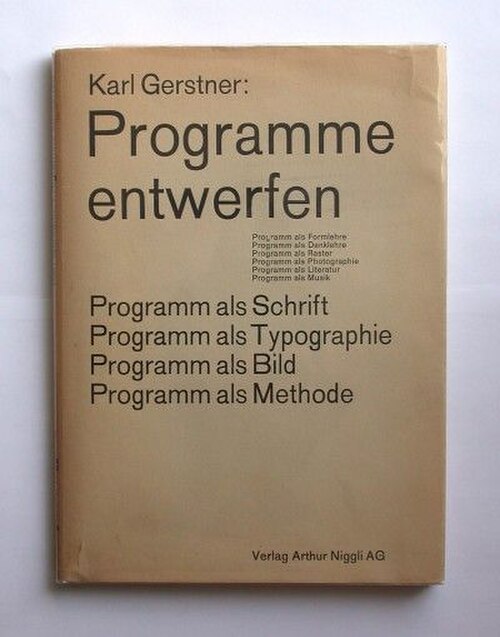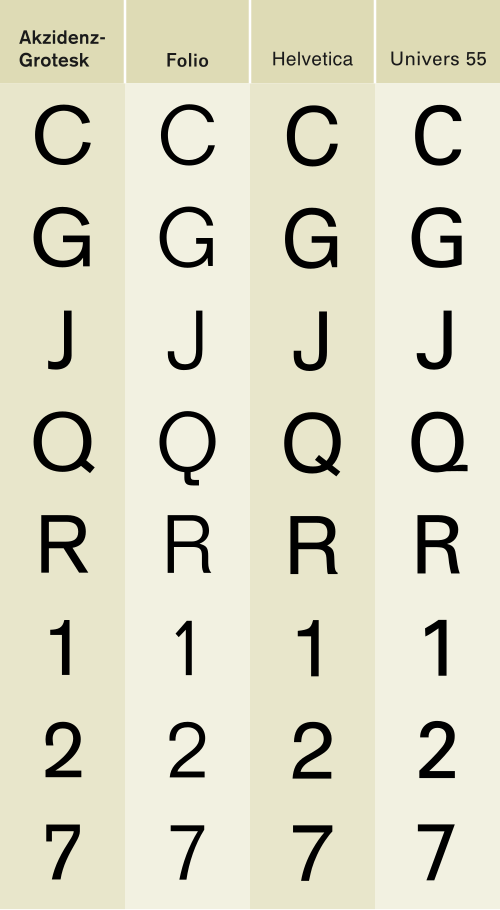
| カテゴリ | サンセリフ |
| 分類 | グロテスク |
| 鋳造所 | H.ベルトルトAG [1] |
| リリース日 | 1898 |
Akzidenz-Groteskは、もともとベルリンのBerthold Type Foundryによってリリースされたサンセリフ 書体ファミリーです。「Akzidenz」は、高級印刷ではなく、宣伝、チケット、フォームなどの商業印刷用の書体として意図されていることを示しており、「grotesque」は当時のサンセリフ書体の標準名でした。
19 世紀後半に誕生したアクチデンツ・グロテスクは、19 世紀にドイツの印刷業界で主流となった、汎用的で飾り気のないサンセリフ体の伝統に属しています。導入後半世紀にわたってあまり知られていませんでしたが、戦後は多くのスイスのグラフィック デザイナーが好む書体として象徴的な地位を獲得し、1950年代から 1960 年代にかけて西側諸国で人気を博した「インターナショナル」または「スイス」デザイン スタイルと呼ばれるようになりました。そのシンプルで中立的なデザインは、その後の多くの書体にも影響を与えました。英語圏の国ではスタンダードとして販売されることがあり、さまざまなデジタル バージョンがBerthold やその他の企業からリリースされています。
語源
アクチデンツ・グロテスクは英語では「jobbing sans-serif」と訳されることが多く、「jobbing」は「仕事に使われる」という意味である。[2]どちらの単語も、当時のドイツ語で書体を表す日常的な用語であった。
Akzidenz は何らかの機会や出来事(「何か起こる」という意味で、高級な社交行事や機会という意味ではない)を意味し[3]、商業印刷の用語として使用されていました。Akzidenzschriftは1870 年代までにこれらの用途を意図した書体を表す一般的な用語になりました。 [3] [4]現代のドイツ語辞書では、広告やフォームなどの作品として説明されています。 [5] [6]この単語の語源はラテン語のaccidentiaで、ルイスとショートはこれを「起こること、偶然の出来事、偶然」と定義しています。 [3] [7]
グロテスク(ドイツ語:Grotesk)は、19世紀前半にサンセリフ体を表す一般的な用語として普及した。1830年頃、ロンドンの活字鋳造業者ウィリアム・ソログッドが、ファン・ストリート鋳造所の見本帳でサンセリフ体を表す名称として導入した。 [8]この名称は、サンセリフ体の「原始的な」感覚、または古代ギリシャやローマの碑文に由来するサンセリフ体を反映している可能性があり、19世紀後半には否定的な意味合いなしに「サンセリフ体」の意味で一般的に使用されるようになった。[8]
デザインの特徴
ほとんどのサンセリフ体と同様に、アクジデンツ・グロテスクは「モノライン」構造で、文字のすべてのストロークの幅が同じです。これにより、シンプルさが感じられ、アール・ヌーヴォー様式の影響を受けた19世紀後半の装飾的なサンセリフ体に見られる装飾や華麗さがありません。[9]現代の書体デザイナーであるマーティン・マヨールは、アクジデンツ・グロテスクとその祖先の全体的なデザインは、19世紀の標準的な印刷用書体であったディド、ワルバウム、およびその追随者などのディドン・セリフ体と文字の形が似ていると述べています。 [10]これは、「a」や「c」などの文字のかなり折りたたまれた開口部で最も顕著です。 [10]アクジデンツ・グロテスクの大文字は幅が広く、幅が比較的均一です。[8]
アクチデンツ・グロテスクの「g」は、他の多くのドイツのサンセリフ体と同様に「1階建て」のデザインですが、ほとんどのセリフ体や小文字の最も初期のサンセリフ体の多くに見られる2階建ての「g」とは異なります。サンセリフ体はロンドンで最初に登場しましたが、19世紀半ば以降にドイツで人気を博しました。[11] [12] ウォルター・トレイシーは、このスタイルの「g」は当時のドイツのサンセリフ体によく見られる特徴であり、 19世紀後半のドイツで長文の印刷にまだ非常に人気があり、1階建ての「g」を縦組みで使用しているブラックレターの伝統に影響を受けたものであると述べています。[ 13]
アクチデンツ・グロテスクの金属活字は、文字間隔や比率を調整して、文字サイズが小さいほど文字間隔を広くするなど、サイズ間でのバリエーションが見られますが、これは金属活字のデザインや彫刻では通常の慣行でした。[ 14 ] [15] [16]さらに、ウェイト間でもバリエーションがあります。カール・ゲルストナーは、1つのサイズ(20pt)を比較しただけでも、ミディアムウェイトとボールドウェイトは、ライトウェイトとレギュラーウェイトとはxハイト、キャップハイト、ディセンダーの長さが異なると指摘しています。 [14] [17]これは19世紀のサンセリフ体によく見られるもので、互いに一致する拡張ファミリーを形成する意図でデザインされたものではありません。[18] [3](1900年代のベルトルトの文献では、ライトウェイトとレギュラーウェイトは互換性があると宣伝されており、当時ライトウェイトは「ロイヤル・グロテスク」と呼ばれていました。[19])アクチデンツ・グロテスクの異なるサイズと重量の比率の違いは、以下で説明するように、元のデザインのさまざまな側面を復活または変更する現代的な適応につながっています。
初期の歴史
アクチデンツ・グロテスクのデザインは、19世紀に作られた汎用サンセリフ体の流派に由来している。[21]サンセリフ体は19世紀後半までにドイツで非常に人気が高まり、さまざまなバージョンを提供する小規模な地方の活字鋳造所が多数存在した。[22] [11]
H.ベルトルトは1858年にベルリンで設立され、当初は機械加工された 真鍮製の印刷用定規を製造していましたが、1893年以降は鋳造金属活字の製造に進出しました。 [23] [24 ] 1920年代以降のベルトルトの出版物には、このデザインは1898年のものと記載されており、[25] [11] [26]この年に同社はこのファミリーに関する2つのデザイン特許を登録しました。[27] [28]
エッケハルト・シューマッハ=ゲブラー、インドラ・クプファーシュミット、ダン・レイノルズによる最近の研究により、アクチデンツ・グロテスクの歴史の多くの側面が明らかになった。アクチデンツ・グロテスクの起源は、1897年にベルトルトがシュトゥットガルトのバウアー・u. Cie書体鋳造所を買収したことにあるようだ(フランクフルトのバウアー書体鋳造所はよく知られているが、これと混同しないように)。バウアー書体鋳造所は、ドロップシャドウ効果のあるサンセリフ体(ドイツ語:Schattierte Grotesk)を最近リリースしたばかりだった。[20] [31]アクチデンツ・グロテスクはこのデザインに基づいているが、ドロップシャドウは削除されている。[31]アクチデンツ・グロテスクに関する2つの意匠特許は1898年4月に申請された。最初は14日にシュトゥットガルトでバウアーによって、次に28日にベルリンでベルトルトによって申請された。レイノルズはベルトルトの記録から、この意匠はシュトゥットガルトで生まれたものであることが判明した。[28] [31]アクチデンツ・グロテスクを紹介する初期の広告には、両方のブランドが共同署名しているものがある。[32] [33] [34]ベルトルトにおけるアクチデンツ・グロテスクに関する初期の言及では、しばしば「Accidenz-Grotesk」という別の綴りが使用されている。レイノルズは、この名前はバウアー&カンパニーの鋳造所が販売した「Accidenz-Gothisch」ブラックレター書体に続くブランド拡張として意図されていたのではないかと示唆している。[35] [36]一般的に、レイノルズは、シャティエテ・グロテスクとアクチデンツ・グロテスクのスタイルは「他の会社の特定の製品のコピーというよりも、当時のサンセリフ書体デザインのアイデアを統合したもののように思われる」とコメントしている。[3]
アクツィデンツ・グロテスクのライトウェイトは、長年「ロイヤル・グロテスク」として別ブランドで販売されていた。このフォントは、1902年から1903年頃にベルトルトによってカットされたようで、業界誌で「新しい、非常に使いやすい書体」として発表され、アクツィデンツ・グロテスクのレギュラーウェイトと組み合わせることができるように寸法が一致すると宣伝された。[26] [37] [19] [25]レイノルズとフロリアン・ハードウィグは、シュマルハルブフェットウェイト(セミボールドまたはミディアムコンデンス)が多くのドイツの活字鋳造所で販売されているファミリーであり、おそらくニューヨークの活字鋳造所から生まれたものであることを文書化した。[38] [39] [40]
ベルトルトの戦後の芸術監督で、事実上アクチデンツ・グロテスクデザインのキュレーターとみなされていたギュンター・ゲルハルト・ランゲは、2003年のインタビューで、アクチデンツ・グロテスクはフェルディナント・ザインハルト活字鋳造所から生まれ、この主張は他の場所でも広く模倣されていると述べた。 [41]これは、実業家で活字鋳造工のフェルディナント・ザインハルトによって確立されたもので、彼はヒエログリフとシリア語の書体の分野での学術的努力で特に有名であったが、1885年に事業を売却していた。 [ 42] [43] [44]クプファーシュミッドとレイノルズは、ベルトルトがザインハルト鋳造所を買収した後、アクチデンツ・グロテスクが会社に登場したことで彼が誤解したのではないかと推測している。[23] [45] [46] [47] [48] [26] [20] [33] [49]レイノルズはさらに、アクチデンツ・グロテスクが発売される10年前の1885年に、ザインハルトが自分の鋳造所をオスカー・マメンとロバート・モージグ、エミール・モージグに売却し、この年以降に彼らのためにさらにフォントを切ったという証拠はないことを指摘している。[44]ランゲがコメントしたように、戦後、ロイヤル・グロテスクの名はプロイセン科学アカデミーの委託を受けたことに由来すると主張されたが、クプファーシュミットは同アカデミーの出版物でその名前が使われているのを見つけることができなかった。[26]
この時期、ドイツではアクツィデンツ・グロテスクに似たスタイルのグロテスク書体が数多く販売されていた。20世紀初頭には、これらが複数のスタイルを組み合わせたより大きなファミリーとしてブランド化されるようになった。[3] [50]競合製品には、フランクフルトのバウアー鋳造所の非常に人気のあるヴィーナス・グロテスク(アクツィデンツ・グロテスクに非常に似ているが、ハイウエストのキャピタルを持つ)や、シェルター&ギーゼッケのコラレ(1階建ての「a」を持つ)などがある。[51] [52] [b](モノタイプ・グロテスク215もこの時期のドイツの書体に基づいています。[54])ゼーマンの1926年の書体ハンドブック(ドイツ語:Handbuch der Schriftarten)は、ドイツで入手可能なすべての金属書体のハンドブックであり、出版当時ドイツで販売されていたサンセリフ書体の幅広い範囲を示しています。[55] [25] 1911年頃までに、ベルトルトはアクチデンツ・グロテスクを完全なファミリーとして販売し始めました。[56] [26] [33]
アクチデンツ・グロテスクは不人気ではなかったようだが、当時最も盛んに販売された書体ではなかったし、ベルトルト自身も特に積極的に販売していたわけではない。[14] 1921年のベルトルトの見本と会社の歴史では、ほとんど弁解するかのように次のように説明されている。「1898年にアクチデンツ・グロテスクが作られ、名声の栄冠を獲得した。この古い書体は、今日ではもっと現代的なスタイルで作られるかもしれないが、独特の生命力を持っており、変更されれば失われてしまうだろう。アクチデンツ・グロテスクの多くの模倣品はどれもその特徴と一致していない。」[36]ベルトルトのアクチデンツ・グロテスクが発売されて間もない時期に珍しい使用者となったのが、詩人のシュテファン・ゲオルクだった。[57]彼は詩を印刷するために、いくつかの特注のアンシャル体代替文字を発注した。 [58] [59] [60]
20世紀半ばの使用